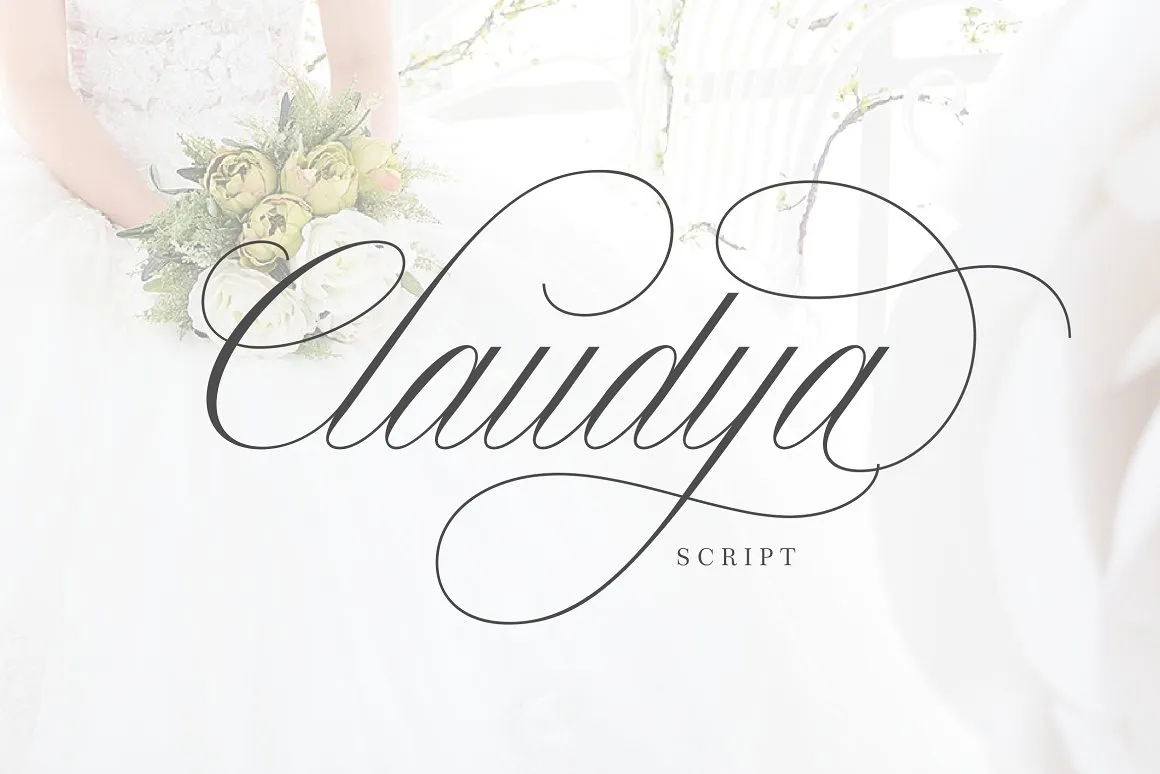
Introduzimos Claudya! Esta fonte foi desenhada por herlannawwi e é maravilhosamente bonita. ClaudyaScript é perfeita para diversas aplicações, como branding, convites de casamento e cartões personalizados, capas de revistas e banners publicitários. Seu amplo conjunto de caracteres alternativos lhe oferece a capacidade de criar designs ainda mais variados e únicos. Estamos ansiosos para que você experimente esta fonte única e elegante que certamente enriquecerá seu trabalho gráfico.